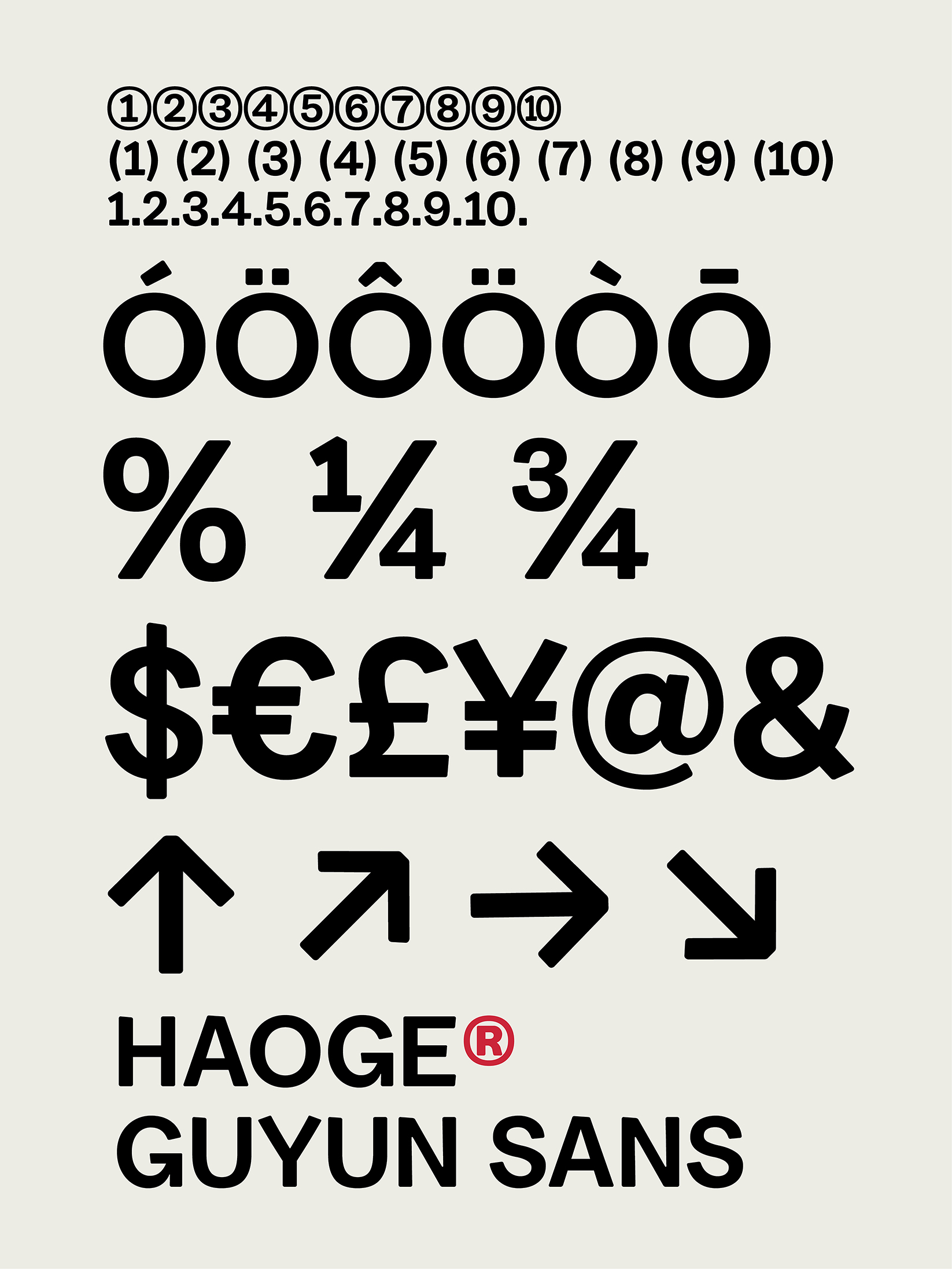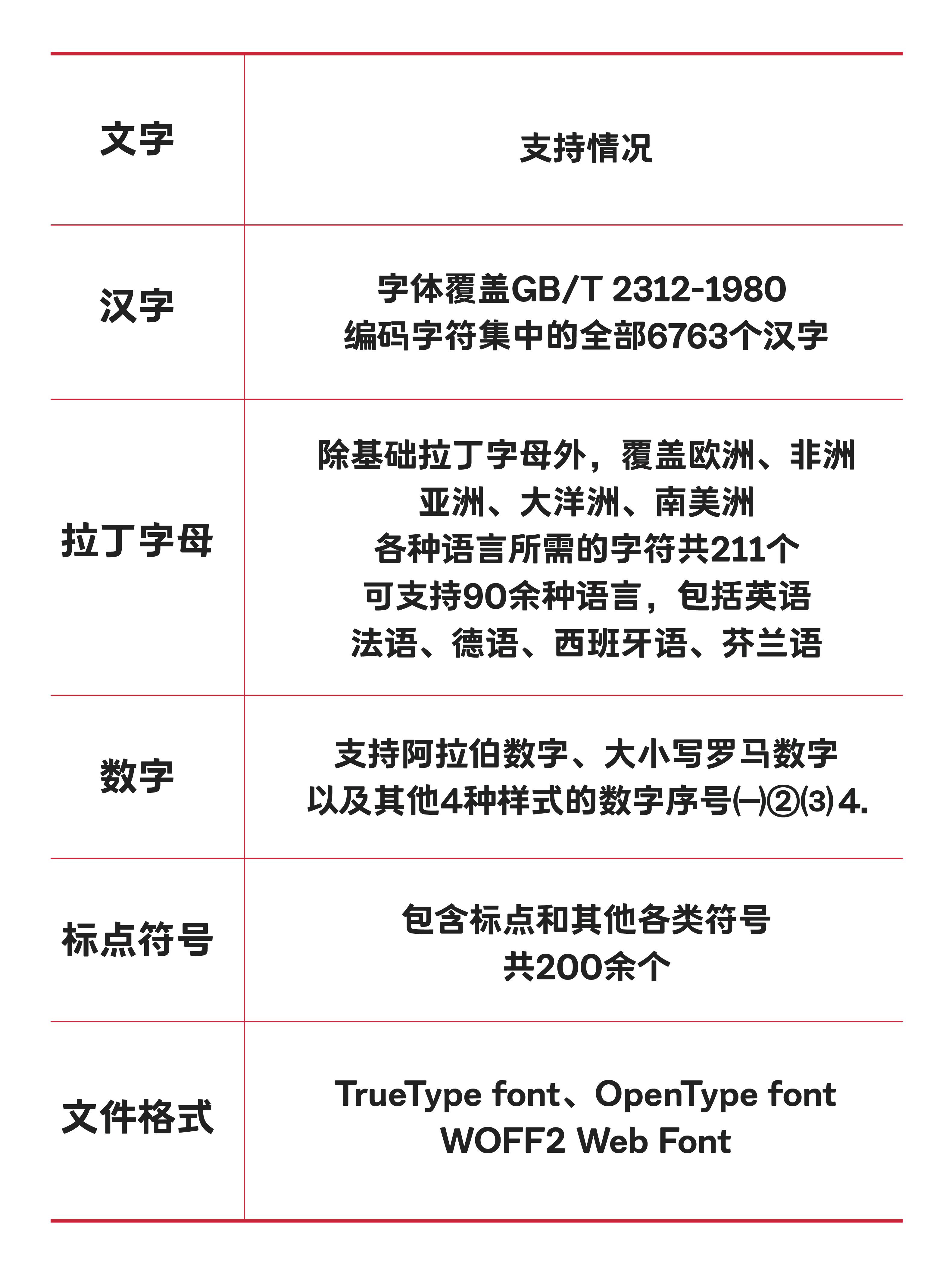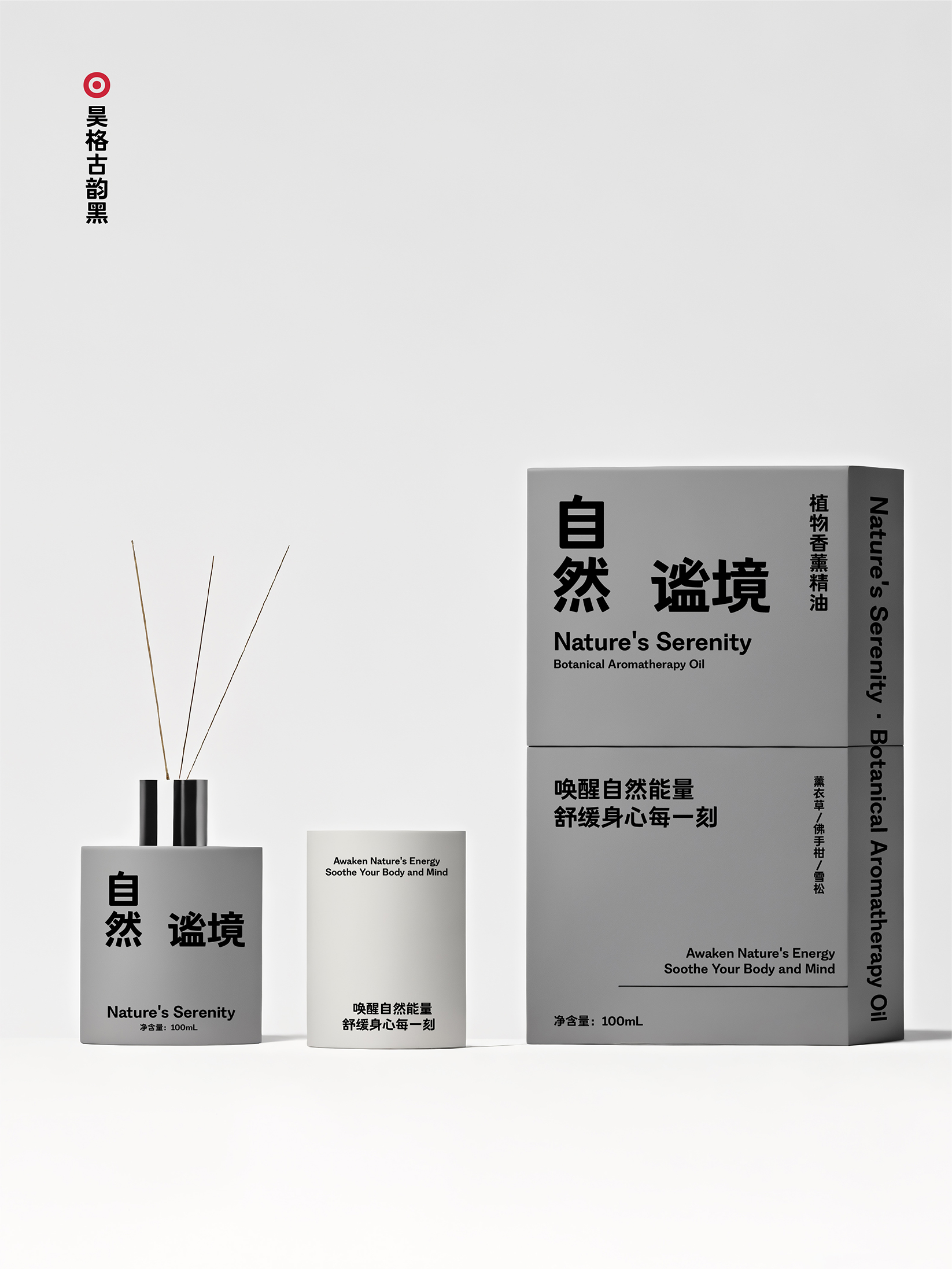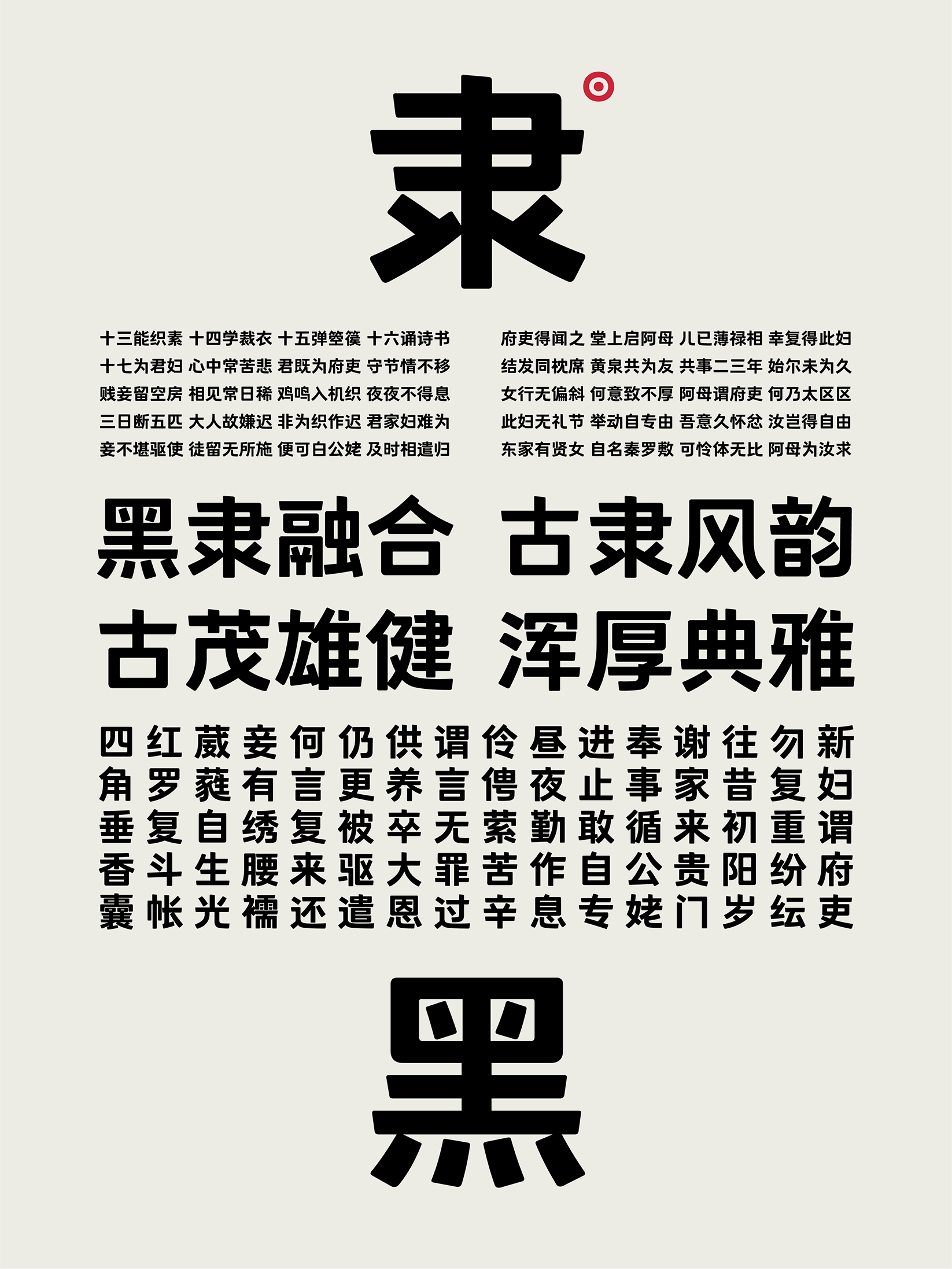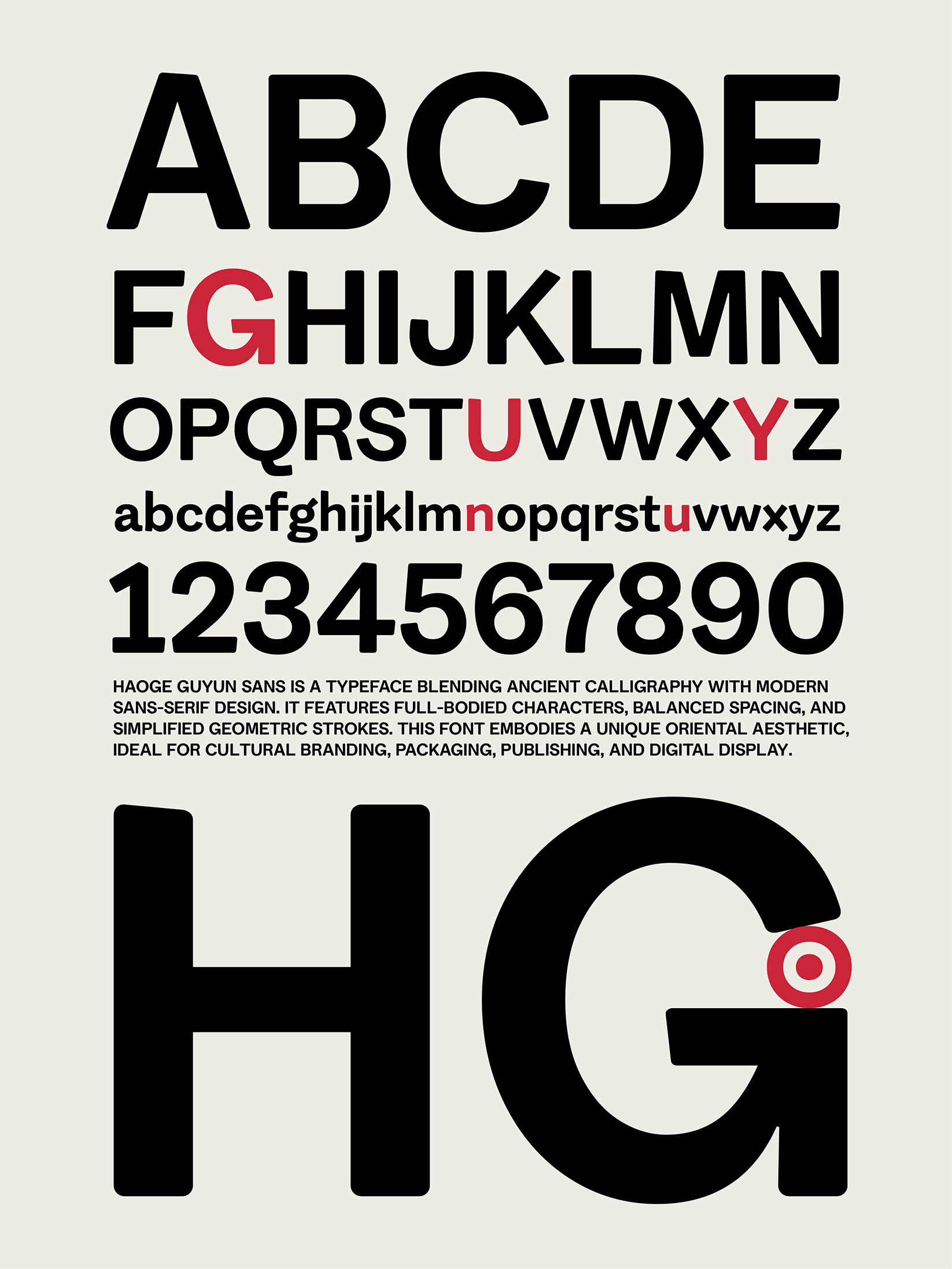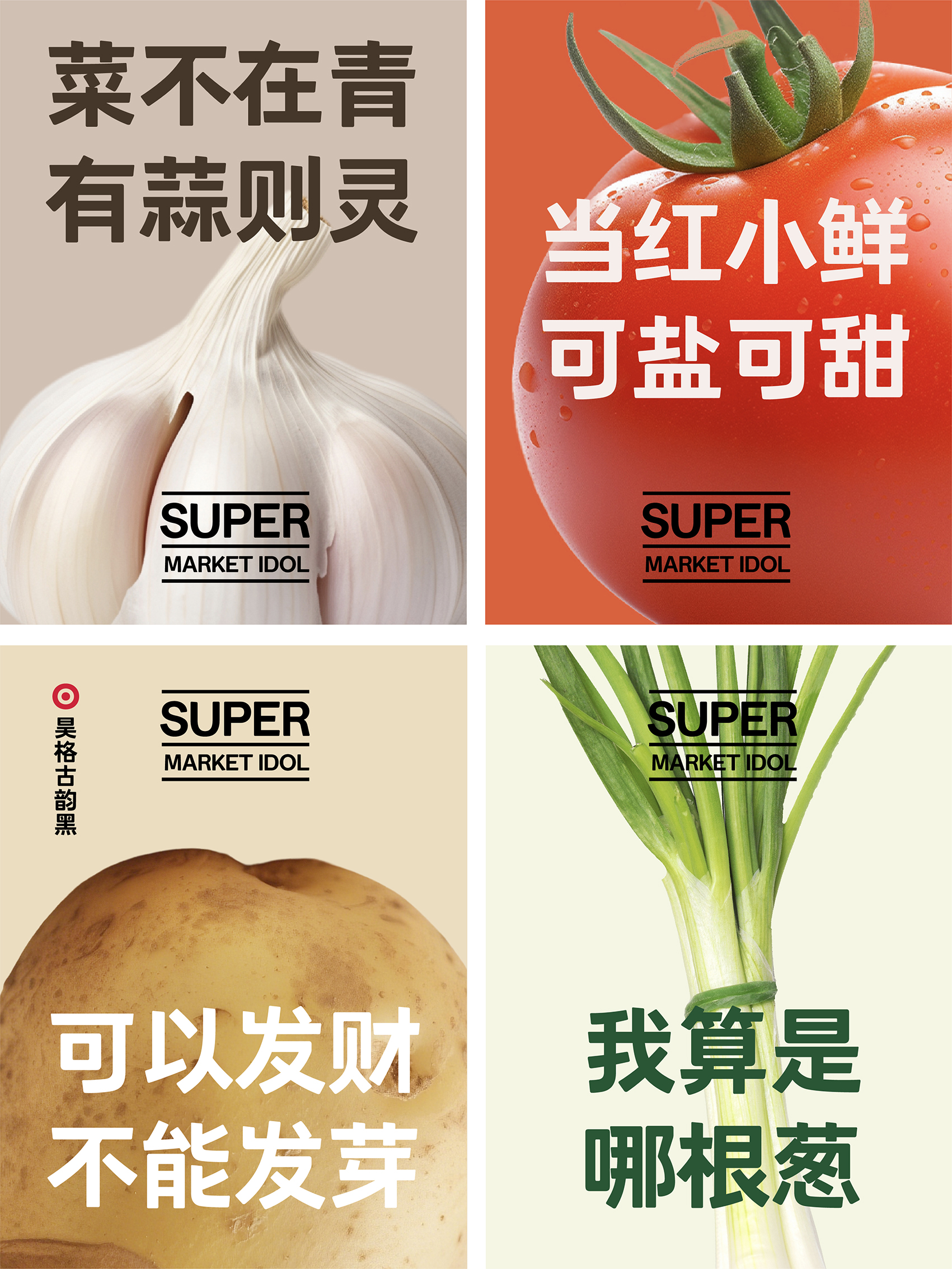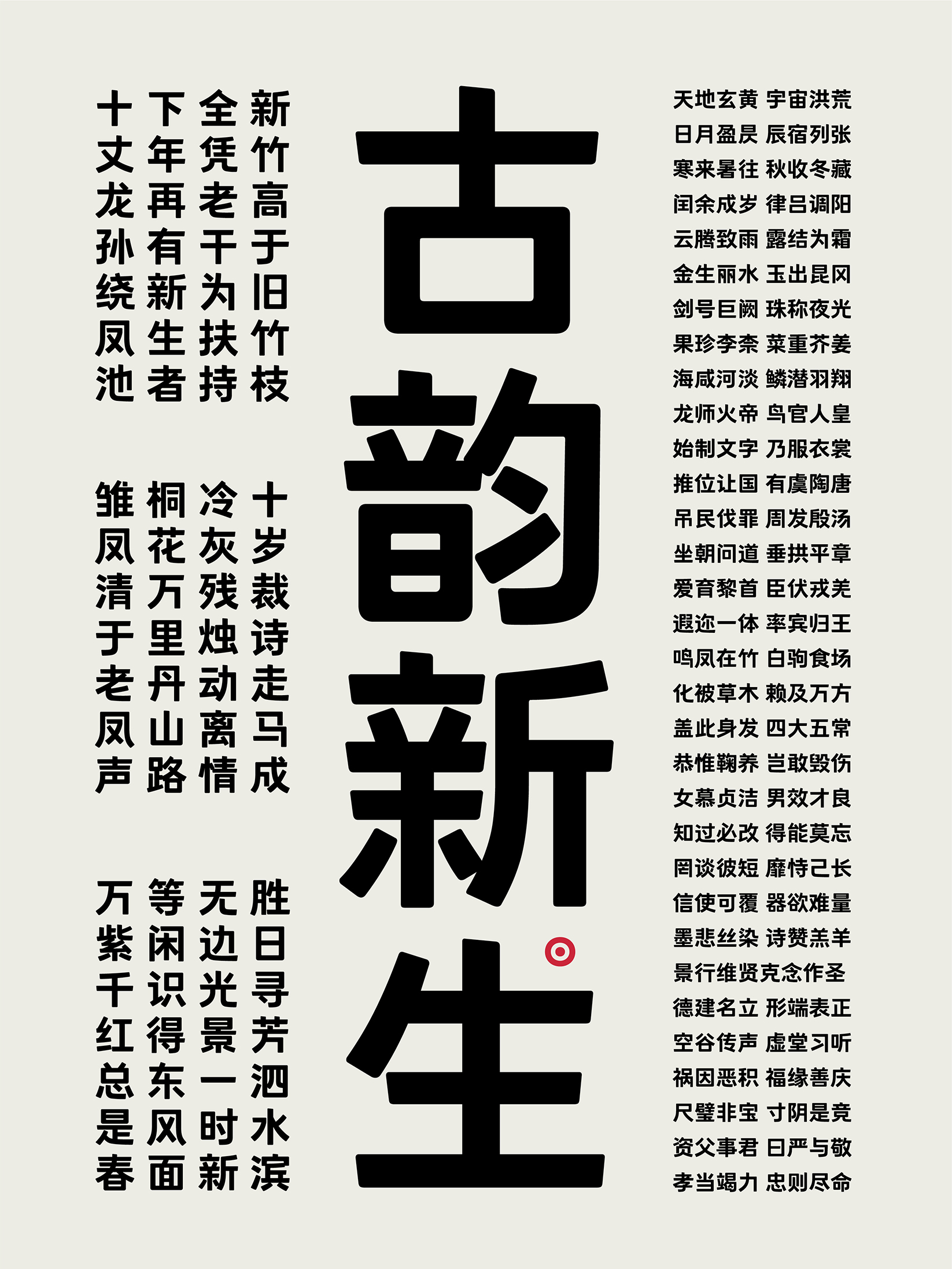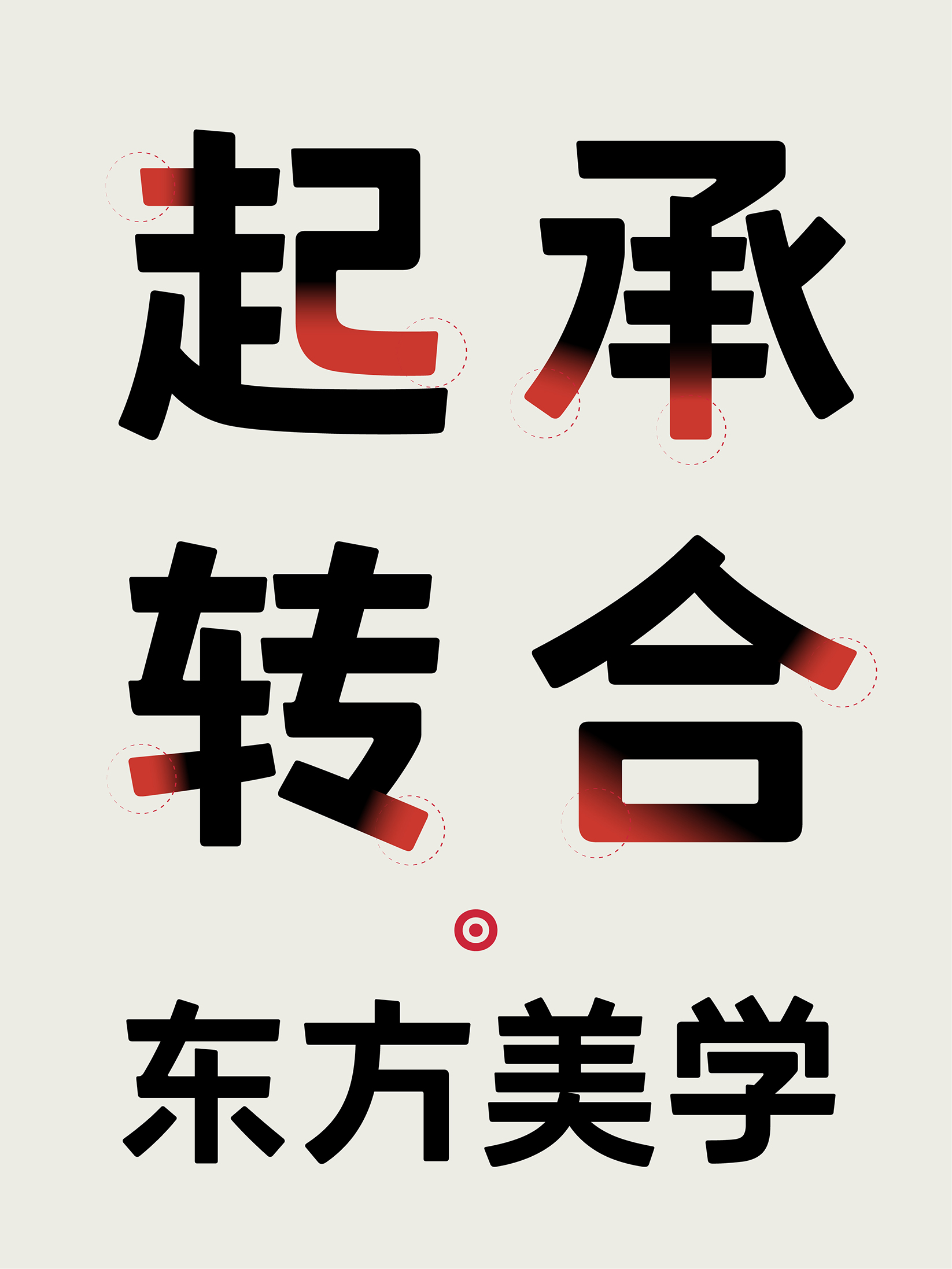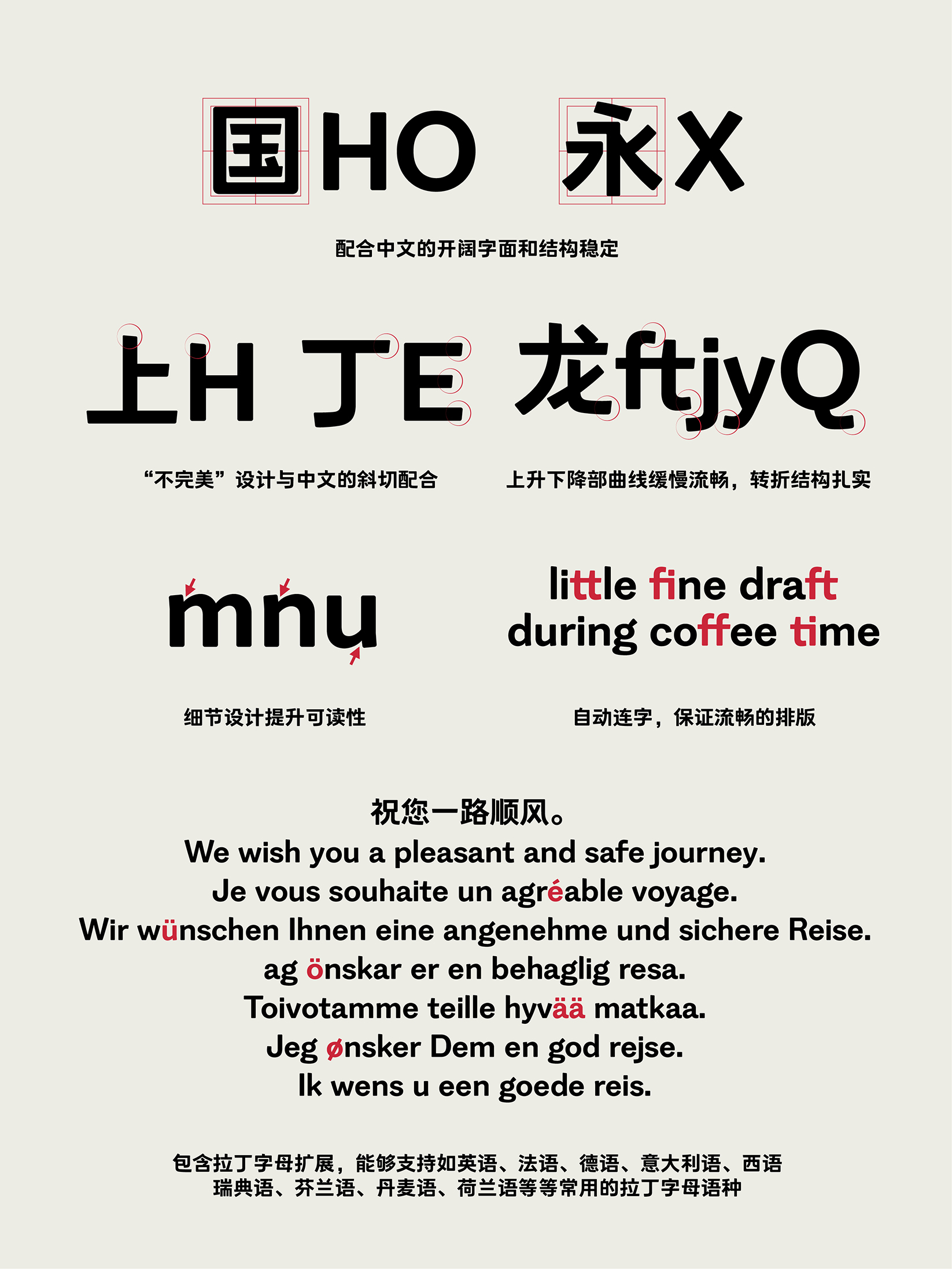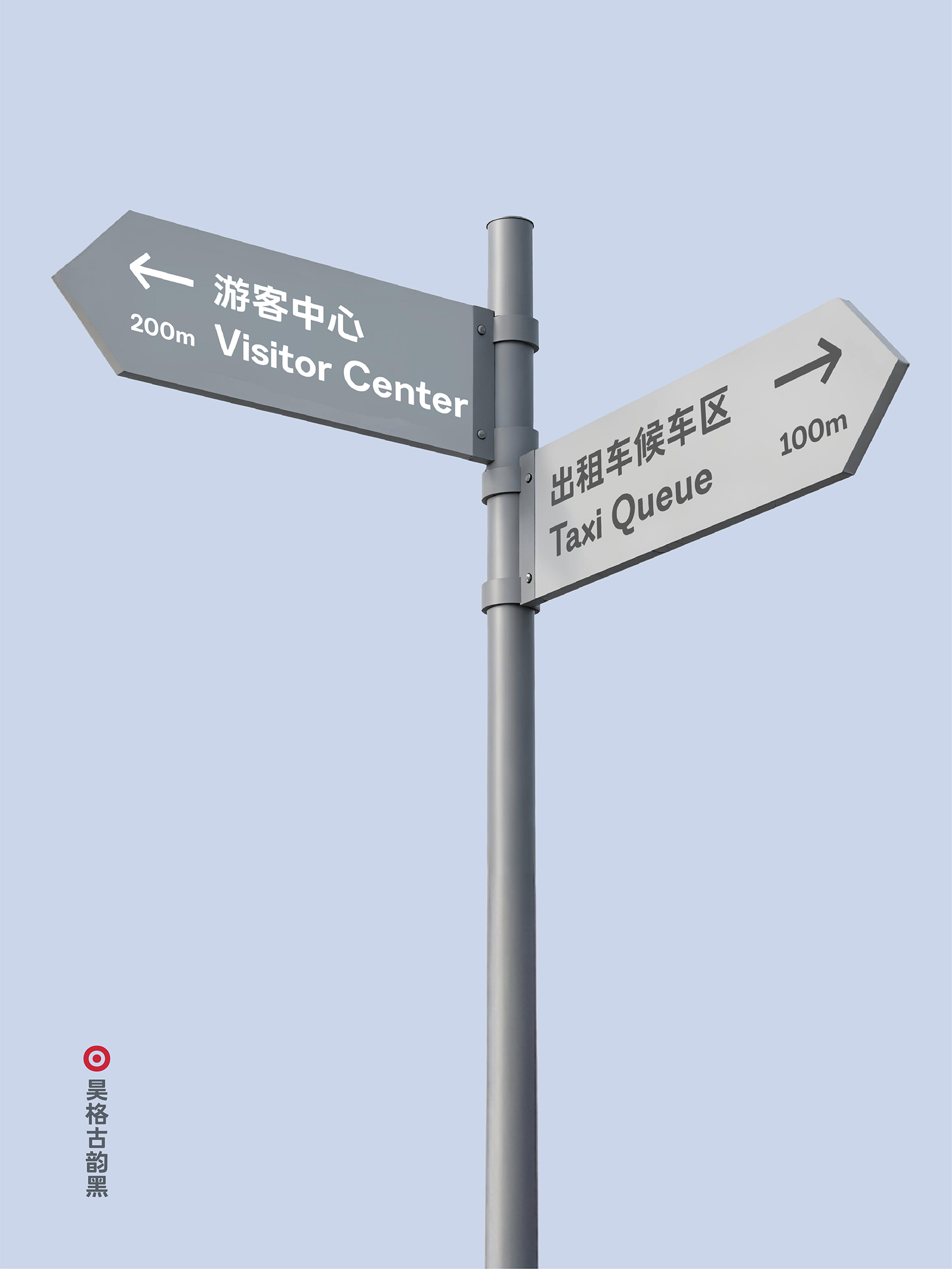
昊格古韵黑
昊格古韵黑,古茂雄健,浑厚典雅,昊格古韵黑是一款具有古隶特征的创意黑体。结构上,将古隶和黑体的结体特征进行融合,字面饱满,重心略高,布白均衡,温和稳定;笔形上,撇,捺,勾,提,转等参考古隶特点,但将形态提炼成简约的几何造型,黑隶融合,传统新生;细节上,起笔收笔的角度和弧度都经过反复推敲,古隶风韵在无衬线黑体中得到了含蓄的彰显;昊格古韵黑整体古拙稳重,返璞归真,呈现出独特的东方美学和文化观念。